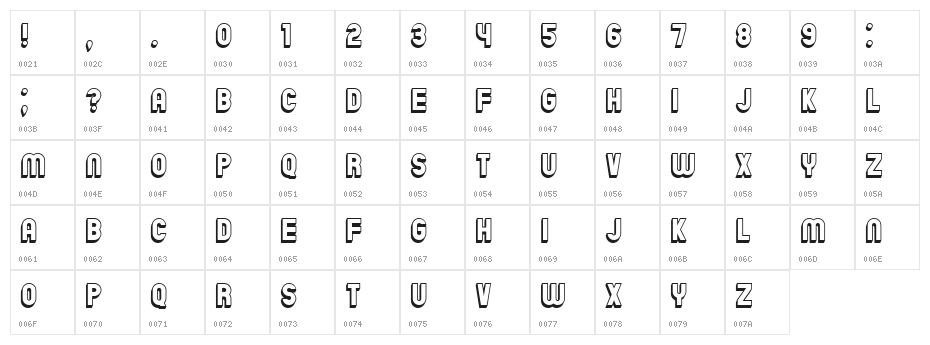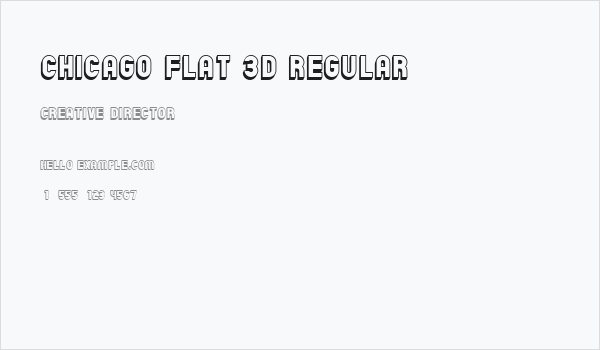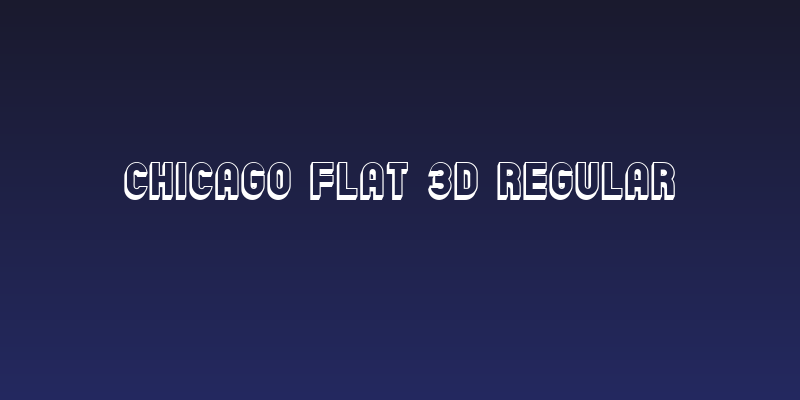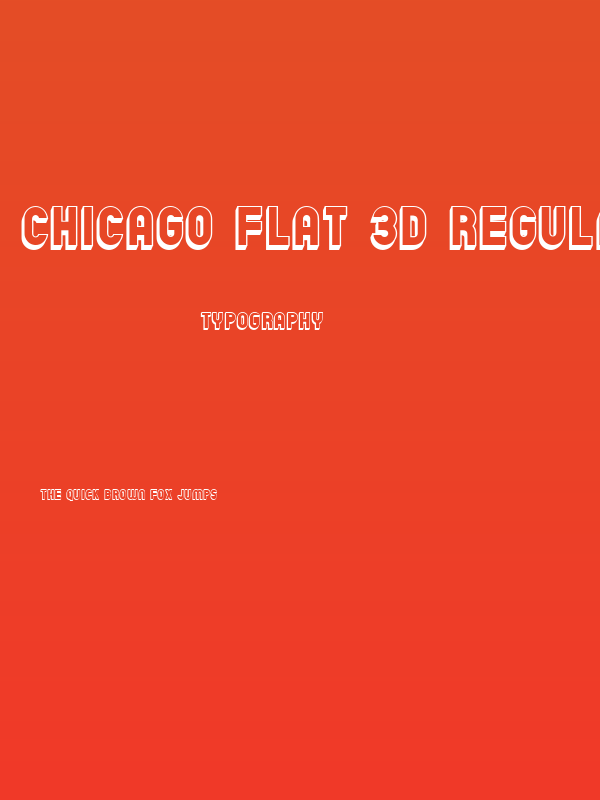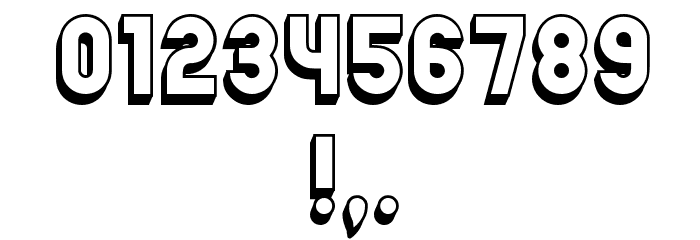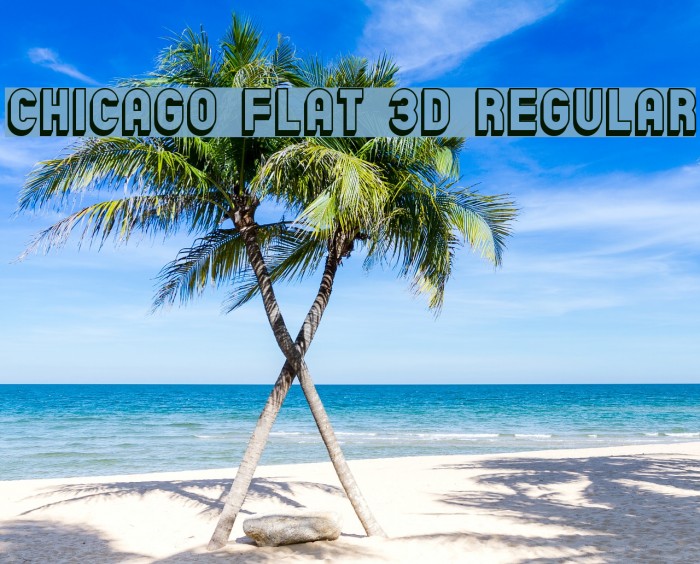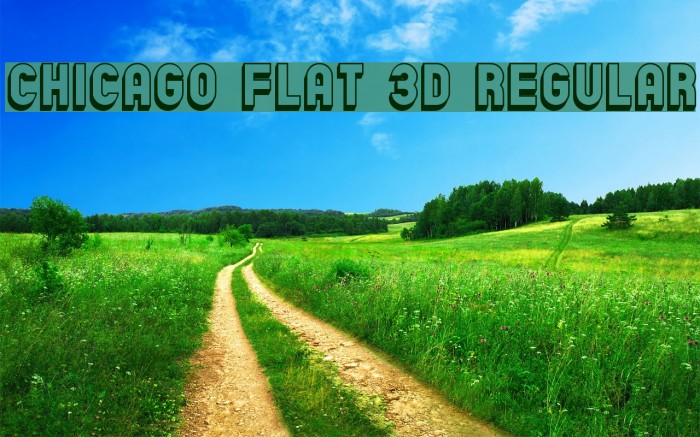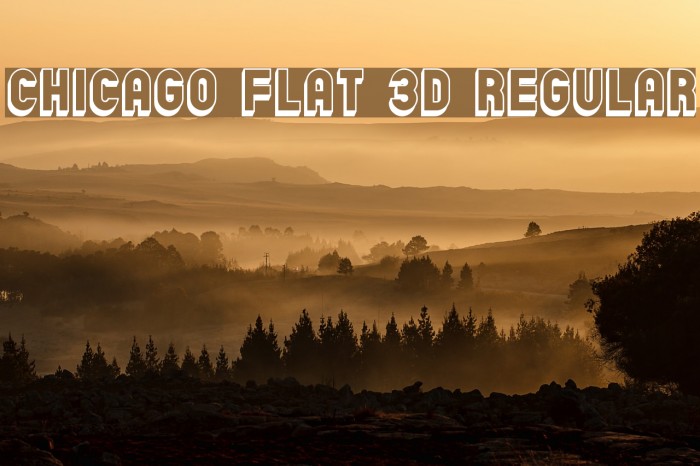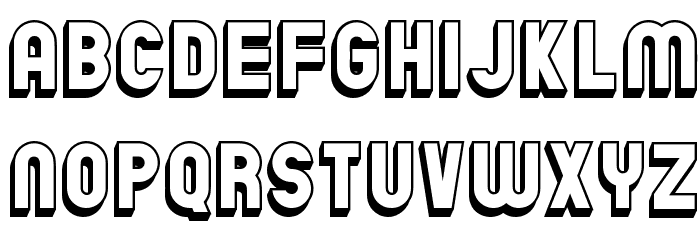
Chicago Flat 3D Regular Font
| Vorgeschlagene Projekte | Ideal for posters, logos, video game graphics, and any design needing a bold, eye-catching typeface. |